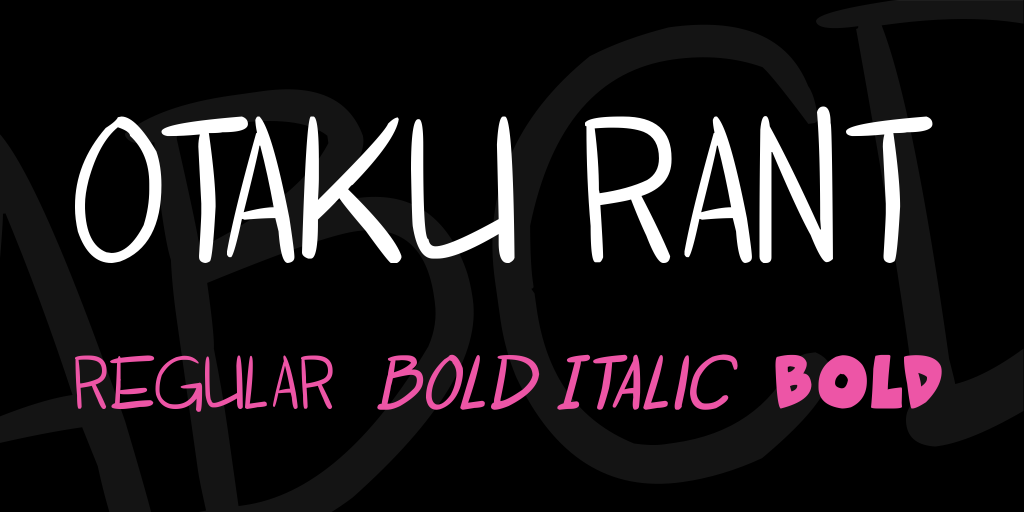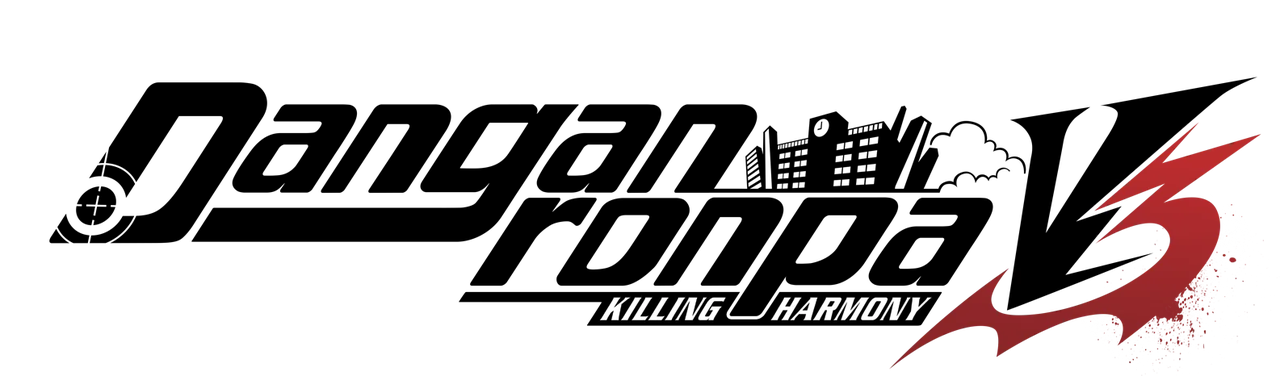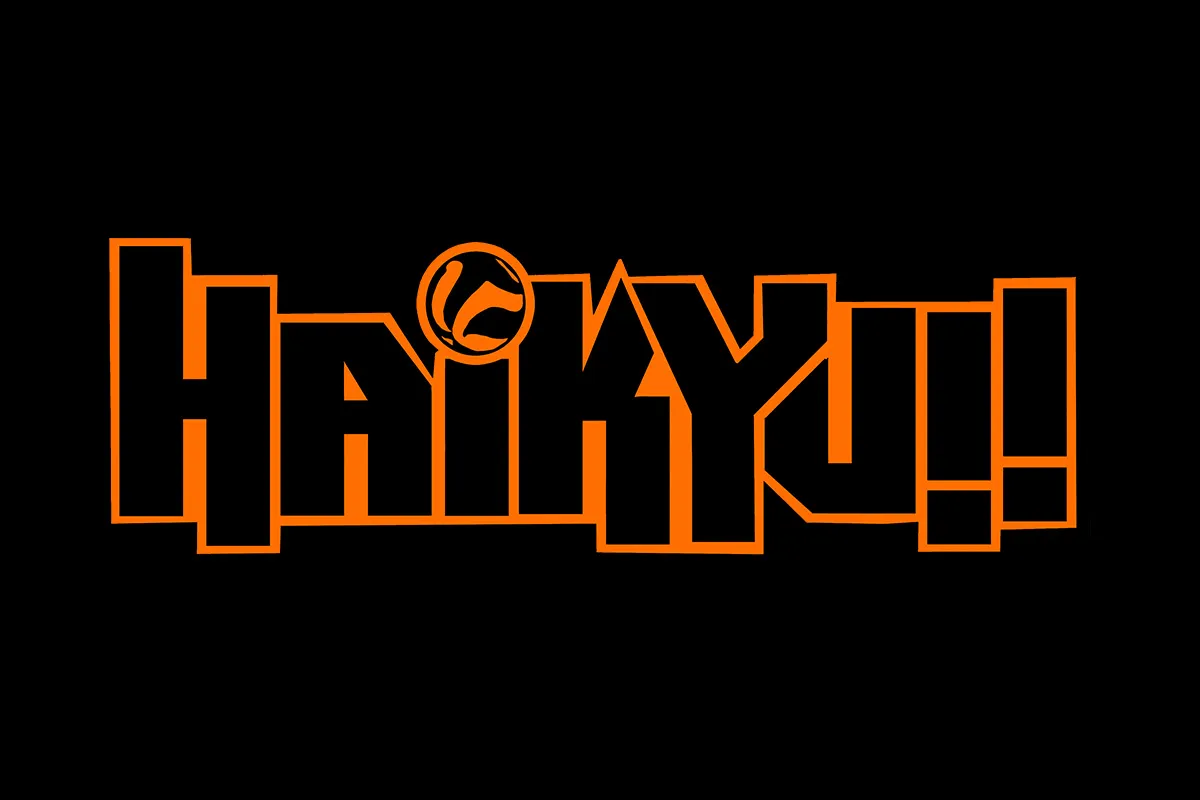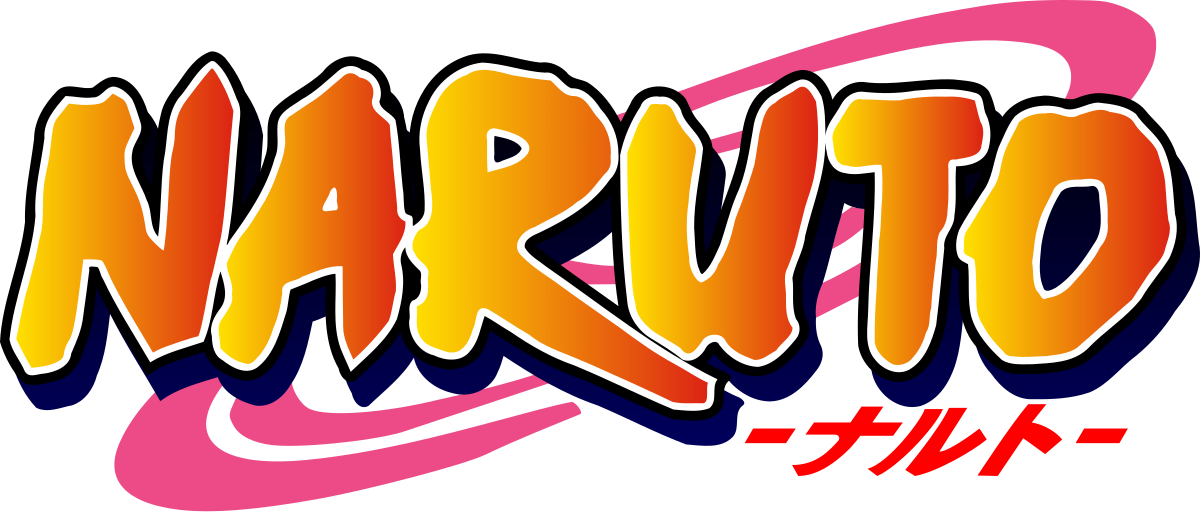
Terokai 5 Alat Terbaik untuk Memilih Fon Anime yang Tepat untuk Projek Anda
Ingin menambah bakat unik pada video anda? Temui cara menggunakan fon anime untuk mencipta tajuk dan grafik yang menarik perhatian yang meningkatkan gaya kandungan anda dan melibatkan khalayak anda.
Memilih fon anime yang betul boleh membuat apa-apa kerja artistik sangat kuat, terutamanya jika seni peminat, jawatan rangkaian sosial, atau bahan pemasaran. Fon reka bentuk yang anime membuat reka bentuk yang hebat dengan menarik penonton dengan rasa dan getaran yang betul. Terdapat begitu banyak fon di luar sana, dan itu meninggalkan satu dalam penyelesaian apabila memilih yang paling sesuai.
Dalam artikel ini, anda akan mengetahui lima alat terbaik untuk digunakan untuk memilih fon anime terbaik untuk projek anda. Daripada perpustakaan fon khusus kepada ciri penyesuaian, alat ini menawarkan cara unik untuk menemui fon yang sesuai dengan penglihatan anda. Sama ada anda memerlukan gaya yang berani, ekspresif atau reka bentuk yang halus dan rumit, alat ini menyediakan kepelbagaian dan fleksibiliti untuk menjadikan projek anda benar-benar unik.
10 fon anime terbaik untuk projek kreatif anda
Fon anime menambah keaslian dan gaya pada projek kreatif yang diilhamkan oleh siri popular. Menggunakan fon bertemakan anime memberikan reka bentuk identiti visual yang unik, menyelaraskannya dengan rancangan dan watak ikonik. Berikut ialah sepuluh fon sari kata anime yang sesuai untuk seni peminat, sepanduk dan bahan promosi.
1. Fon Naruto
Fon ini meniru gaya berani dan bertenaga logo Naruto. Dengan penampilan sapuan berus yang unik, ia membawa rasa aksi dan pengembaraan kepada reka bentuk, sesuai untuk projek yang diilhamkan oleh tema yang sengit dan dinamik.
Naruto Font
2. Fon Anime Ace
Anime Ace ialah fon komik terkenal yang digunakan secara meluas dalam sari kata manga dan anime. Rupa yang bersih dan boleh dibaca menjadikannya sesuai untuk reka bentuk berat teks, seperti panel komik atau dialog dalam ilustrasi.
Anime Ace
3. Fon Nota Kematian
Fon Nota Kematian mempunyai gaya yang gelap dan dramatik, merakam sifat menegangkan dan menakutkan siri ini. Fon ini sesuai untuk projek yang diilhamkan seram atau thriller, menambah suasana misteri.
Death Note Font
4. Fon Evangelion
Diinspirasikan oleh Neon Genesis Evangelion, fon ini mempunyai rupa yang anggun dan futuristik. Ia sesuai untuk tema sci-fi atau cyberpunk, meningkatkan projek yang bertujuan untuk rasa moden dan berteknologi tinggi.
Neon Genesis Evangelion
5. Fon Sailor Moon
Fon Sailor Moon mempunyai reka bentuk ajaib dan suka bermain yang mencerminkan daya tarikan siri ini. Ia berfungsi dengan baik untuk projek feminin, aneh, seperti jemputan, grafik acara atau parti bertema.
Sailor Moon font
6. Fon Haikyuu
Fon Haikyuu menangkap tema sukan bertenaga tinggi siri ini. Ia berani dan dinamik, sesuai untuk reka bentuk berkaitan sukan atau mana-mana projek yang bertujuan untuk menyatakan semangat dan aksi.
Haikyuu font
7. Fon Danganronpa
Reka bentuk fon yang tegang dan tidak konvensional ini mencerminkan misteri dan drama psikologi Danganronpa. Ia sesuai untuk projek yang melibatkan tipu daya atau kelainan yang tidak dijangka.
Danganronpa Font
8. Fon My Hero Academia
Fon ini mencerminkan semangat heroik My Hero Academia, menambahkan rupa yang kuat dan memberi kesan kepada mana-mana projek bertemakan aksi. Ia sangat sesuai untuk reka bentuk yang berani dan menarik perhatian.
My Hero Academia
9. Fon Haiwan Kesayangan
Suka bermain dan serba boleh, Fon Binatang sesuai dengan pelbagai tema yang diilhamkan oleh anime. Fon ini berfungsi dengan baik untuk projek kasual dan menyeronokkan di mana nada ringan diperlukan.
Pet Fonts
10. Keluarga Fon Anime Otaku Rant
Keluarga fon ini termasuk pelbagai gaya, menjadikannya serba boleh untuk genre anime yang berbeza. Ia adalah pilihan fleksibel yang membolehkan percubaan merentas genre.
Otaku Rant Anime Font Family
Menggunakan fon ini boleh membantu menambah personaliti dan bakat pada projek yang diilhamkan anime, menjadikannya tidak dapat dilupakan dan menarik secara visual.